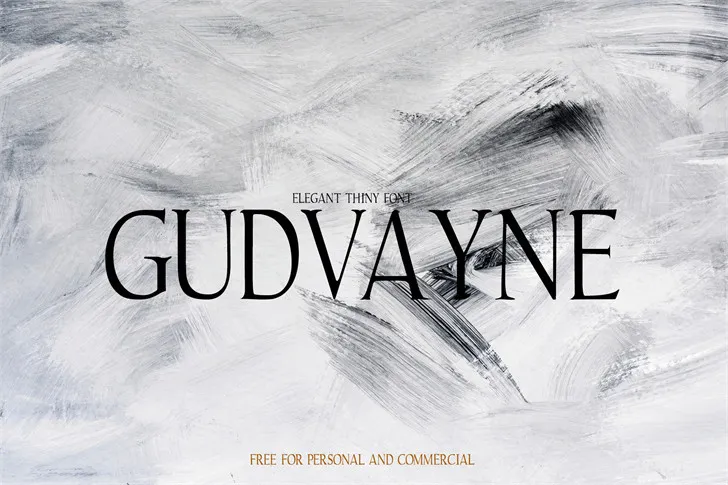
A Gudvayne Font é uma elegante serif que encanta designers a quem ela se destina. Desenvolvida pelo designer 0001themes, esta fonte combina linhas modernas e serifs vintage num contraste perfeito, proporcionando um toque de sofisticação sem perder sua simplicidade. Seja para nomes ou textos legíveis no plano da página, a Gudvayne é uma escolha versátil que adorna qualquer projeto. Com seu design simples e elegante, essa fonte torna o texto fácil de ler em qualquer aplicação visual. Uma compra que não deixará você insatisfeito, a Gudvayne se torna um acréscimo valoroso à sua coleção de fontes. Não hesite – experimente a Gudvayne para incorporar esse estilo único no seu trabalho criativo.